早安,這是小型欄目《遊戲漢化原創字體鑒賞》,關注於早期只在遊戲漢化中出現的點陣字體。雖然說此欄目是專注於“漢化”遊戲的字體,不過在這篇小專欄我想把目光看向一款鮮為人知的主機的原創遊戲的字體。
此次要介紹的字體,來自第一款臺灣自主研發生產的中文遊戲機《Super A’can》(大概也是世界上最快爆s的主機﹙那也比小霸王胎s腹中的強﹚)的第一方遊戲《邪惡之子》。
圖:《邪惡之子》標題畫面。
這台遊戲機的中文編碼有別於常見的Big5、或有些臺灣街機機臺使用的GB12345-1990(嗯?),多採用的是以注音符號排序的遊戲內之所有文字。遊戲內也無輸入法,要自己從表中找。
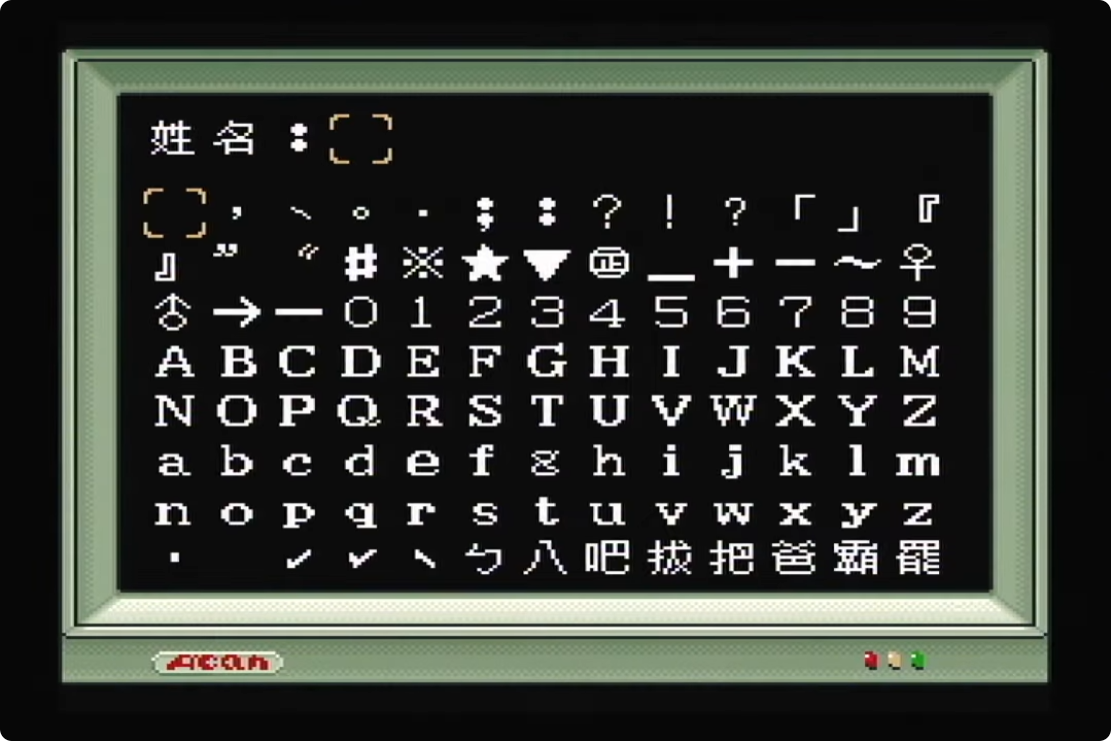
圖:遊戲內姓名輸入介面。來源:Diskman。
此字體是當時少有的11Px點陣,包含2,062字,重覆字1字(挺
)。說實話我個人還挺喜歡這款字體的,重心、灰控、中宮、筆划簡省都算洽到好處,特別是他的筆划簡省,很多字的處理方式我都很喜歡。一些字還有類似宋體的特徵,又參雜手寫韵味,在遊戲顯示中富有趣味性。
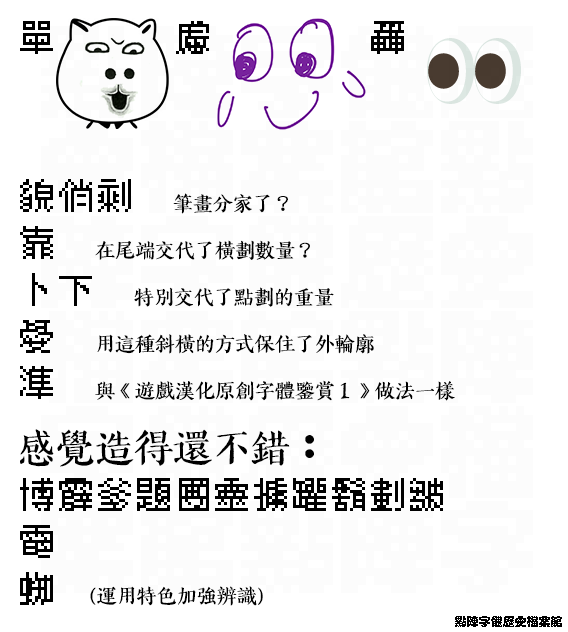
圖:筆者認為一些值得一談的字。
在小點陣字中,有時糊一下反而是可以增加識別度的,但是這款字仍可以保持灰度的同時稍稍縮小中宮,屬實不易。(有一說中式審美比較不喜歡看大中宮大字面的字?反正這款字在這點處理得不錯。)
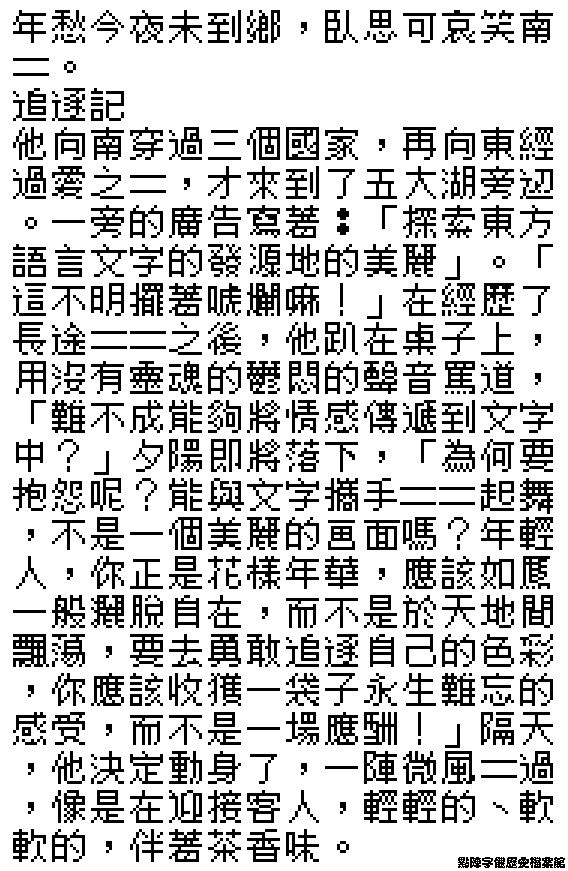
圖:字體樣張。
特色上與天堂鳥相似,皆是偏向手寫風的宋體字形。在有空間時也把一些宋體特徵繪掣出來
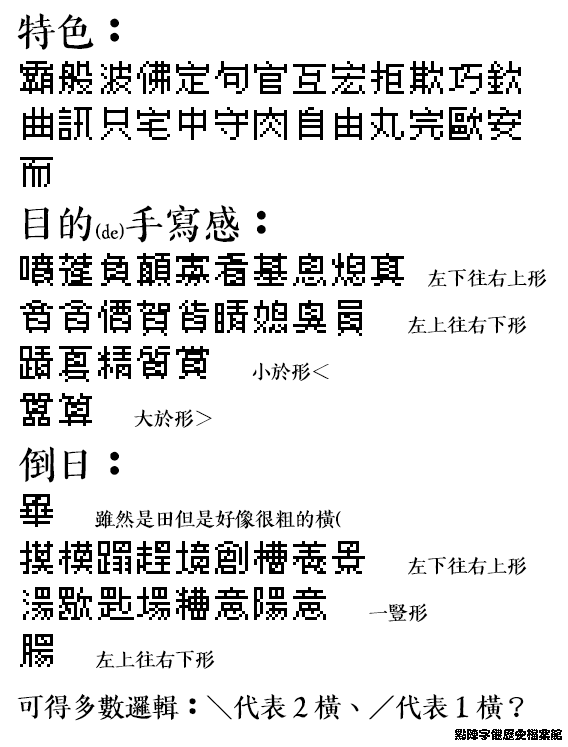
圖:個人認為有點特色的字。(意其實可以連上立就不用調整為豎橫啦~)
比較可惜的是在一些複雜的字上,這款字採取的策略是用俗字表示,而不是用點陣簡化技巧去處理,偶爾也有些錯字。不過也不影響遊戲,不是嘛?
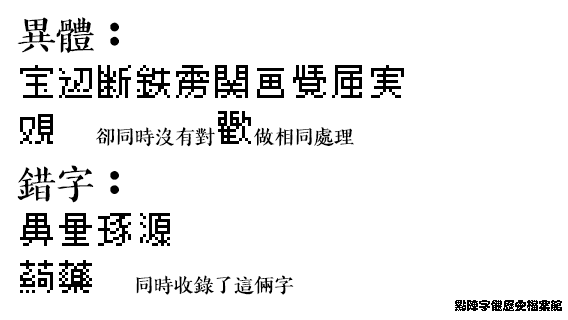
圖:收錄的異體字及錯字。
此字體全角ASCII及注音部分應是壓自ET 24Px的(ET系列之後再開新小欄目介紹。)
圖:此字與ET的對比。
個人感覺這款字體與此遊戲是挺搭配的。在此附一些實機畫面。
如果這篇小專欄在上週發佈,就不會有以下內容。
筆者在泰騰的《青澀的果實》中也發現了此字體,甚至可能有2款(很類似)。可惜在遊戲原文件內只提取到1款,與之前所述邪惡之子相同。可能另一款他們已經做為圖片存儲了。不過說實話,這款遊戲及發行商真的非常神秘,在網上僅有一人撰文,而文中表示……在他之前“完全沒有半點資料”,是在我日常涉獵時偶然發現的!
圖:遊戲內出現的兩款字體對比。
此字體在遊戲內採用Big5排序遊戲內用字子集,收錄2,596個字符。一樣,在邪惡之子有出現的簡俗字,這裡一樣有。因為蒐集到的字數多了,這些再展示一些。
圖:簡俗字展示。
就此,筆者懷疑此為一真實存在的完整字庫,奈何從字體到遊戲,資料都少之又少。在此先做紀錄,待日後補充。